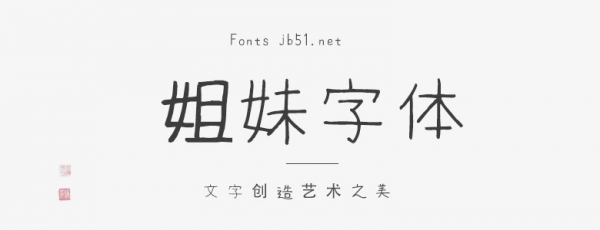
姐妹字體一種免費(fèi)的等寬 TrueType 字體,可再現(xiàn)柔和的手寫(xiě)字符。據(jù)作者介紹,該字體是按照像妹妹一樣努力認(rèn)真寫(xiě)字的女孩形象創(chuàng)作的,看起來(lái)就像是高年級(jí)小學(xué)或初中女生在筆記本上精心書(shū)寫(xiě)的。以手寫(xiě)風(fēng)格完成。它包含幾乎所有半角和全角字母數(shù)字字符、平假名、半角和全角片假名、JIS 1 級(jí)和 2 級(jí)漢字、希臘字母、俄語(yǔ)字母和擴(kuò)展?jié)h字,因此可用于廣泛的用途。目的范圍。它可以免費(fèi)用于個(gè)人和商業(yè)目的,并且只要免費(fèi)分發(fā)就允許重新分發(fā)。